50 แบบอักษรควันที่ดีที่สุดสำหรับนักออกแบบ
เผยแพร่แล้ว: 2022-06-30คอลเลกชันของ แบบอักษร Smoke ที่ดีที่สุด ที่นักออกแบบสามารถใช้เพื่อปรับปรุงการสร้างสรรค์ของพวกเขา
นักออกแบบครั้งแล้วครั้งเล่าสำหรับโครงการและงานศิลปะต่างๆ แบบอักษรควัน มีเอกลักษณ์เฉพาะตัว ใช้สำหรับหัวเรื่อง ชื่อเรื่อง และคำบรรยายอย่างมีประสิทธิภาพ
แบบอักษรควันช่วยเพิ่มรสชาติให้กับข้อความและมีศักยภาพที่จะดึงดูดความสนใจของผู้ชมได้ทันที
นี่คือคอลเลกชันของแบบอักษร Smoke ที่ดีที่สุดที่คุณสามารถใช้เพื่อทำให้การออกแบบของคุณดูมีเอกลักษณ์แต่น่าดึงดูด
แบบอักษรการสูบบุหรี่
แบบอักษรสไตล์วินเทจที่ดูดีซึ่งคุณสามารถใช้ออกแบบโครงการของคุณได้ แบบอักษรนี้ดูทันสมัยบนพื้นหลังใดๆ คุณสามารถใช้แบบอักษรนี้ในการออกแบบการ์ดอวยพร โครงการที่เกี่ยวข้องกับการโฆษณา และในโครงการออนไลน์ใดๆ ก็ได้
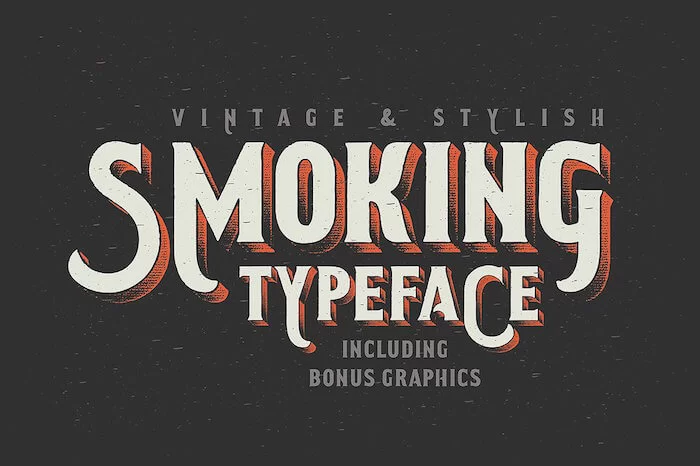
อัลฟ่า สโมค
ด้วยจำนวนสัญลักษณ์ 72 แบบอักษร Alpha Smoke ไม่อยู่ในคลาสครอบครัวที่ระบุ แบบอักษรกึ่งหนานี้มีความกว้างปานกลาง (ปกติ) แบบอักษรเป็นไปตามสไตล์ Mac ตัวหนาและมีลักษณะลวดลายที่ร่างไว้
มีท่ายืนตรงและมีความกว้างปกติ อย่างไรก็ตาม มันไม่ใช่โมโนสเปซ คุณสามารถดาวน์โหลดแบบอักษรนี้ได้ที่นี่
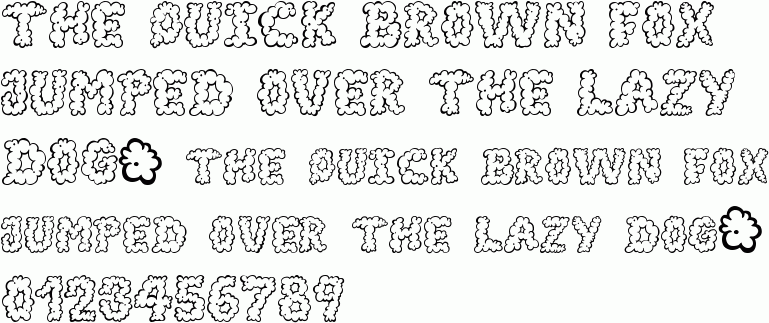
หลังจาก Cheret Bold
แบบอักษรเป็นของตระกูล 'ละติน (ข้อความและจอแสดงผล)' และเป็นไปตามสไตล์ mac ตัวเอียง ไม่อยู่ในกลุ่มครอบครัวที่ระบุใด ๆ และมีน้ำหนักตัวหนา
แบบอักษรมีความกว้างปานกลาง (ปกติ) และมีลวดลายที่เป็นธรรมชาติ มีสัญลักษณ์จำนวน 176 มันไม่ใช่โมโนสเปซ สามารถดาวน์โหลดแบบอักษรนี้ได้ที่นี่
รถไฟของเล่น
แบบอักษรมีจำนวนสัญลักษณ์ 87 แบบอักษรนี้ไม่อยู่ในประเภทครอบครัวที่ระบุและเป็นแบบกึ่งน้ำหนักเบา มีความกว้างปานกลาง (ปกติ) ฟอนต์ตามสไตล์ mac ตัวหนา
สไตล์ serif และรูปแบบ arm สำหรับฟอนต์นั้นยังไม่ได้รับการแก้ไขและสามารถเป็นอะไรก็ได้ แบบอักษรนี้สามารถดาวน์โหลดได้ฟรีที่นี่
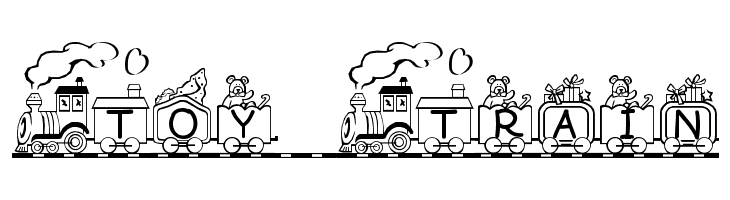
ใบหวาน
ฟอนต์ที่มีสัญลักษณ์จำนวน 219 อันไม่อยู่ในคลาสครอบครัวที่ระบุ เป็นแบบอักษรกึ่งน้ำหนักเบาที่มีความกว้างปานกลาง (ปกติ)
มีรูปแบบของธรรมชาติปกติและไม่เว้นระยะ มันเป็นไปตามสไตล์ Mac ตัวหนาและสามารถดาวน์โหลดได้ ที่นี่
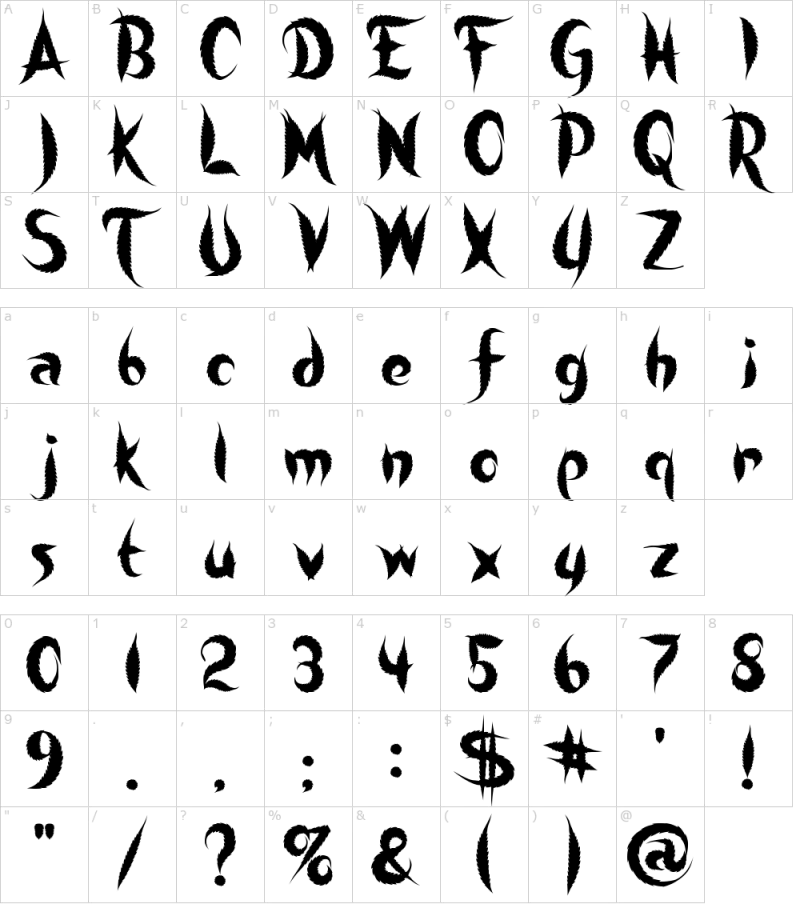
PotLand
แบบอักษรกึ่งน้ำหนักเบานี้เป็นไปตามสไตล์ Mac ตัวหนา ไม่อยู่ในคลาสครอบครัวที่ระบุและมีจำนวนสัญลักษณ์ 219 เป็นแบบอักษรที่ได้รับอนุญาต (มีการป้องกัน) และไม่เว้นวรรค
แบบอักษรนี้มีความกว้างปานกลาง (ปกติ) สามารถดาวน์โหลดได้ที่นี่
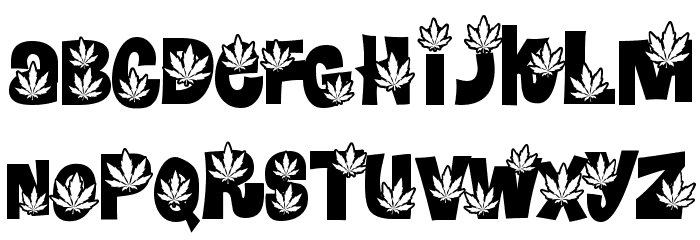
รอยัล อินเฟอร์โน
แบบอักษรเป็นของตระกูล 'ละติน (ข้อความและจอแสดงผล)' และไม่เว้นวรรค มีสัญลักษณ์จำนวน 153 และไม่ได้อยู่ในกลุ่มครอบครัวที่ระบุ
แบบอักษรมีน้ำหนักปานกลาง (ปกติ) และความกว้างกึ่งย่อ มันเป็นไปตามสไตล์ Mac ตัวหนาและมีรูปแบบของธรรมชาติเป็นประจำ ฟอนต์นี้สามารถดาวน์โหลดได้ที่นี่
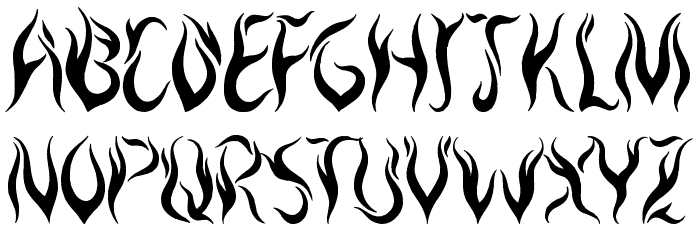
Smoke In The Woods
แบบอักษรมีจำนวนสัญลักษณ์ 91 และอยู่ในคลาสตระกูล 'Slab serifs' มีน้ำหนักตัวหนาและความกว้างที่ควบแน่น มันเป็นไปตามสไตล์ Mac ตัวหนาและมีรูปแบบตัวเอียง
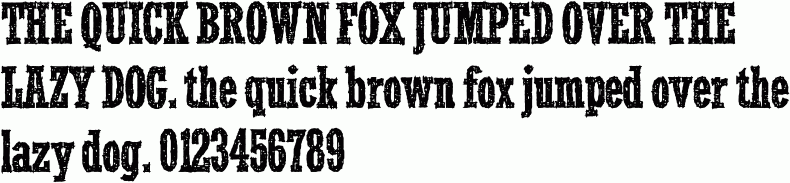
แบบอักษรควัน
นี่คือชุดแบบอักษรควันที่สมบูรณ์ แบบอักษรแต่ละแบบมาแยกกันในไฟล์ PNG ที่มีพื้นหลังโปร่งใส
คุณสามารถดาวน์โหลดแบบอักษรและแก้ไขได้ในโปรแกรมแก้ไขแบบอักษร นี่อาจเป็นตัวเลือกแบบอักษรที่ดี หากคุณต้องการให้งานออกแบบของคุณดูมีควันมากขึ้น
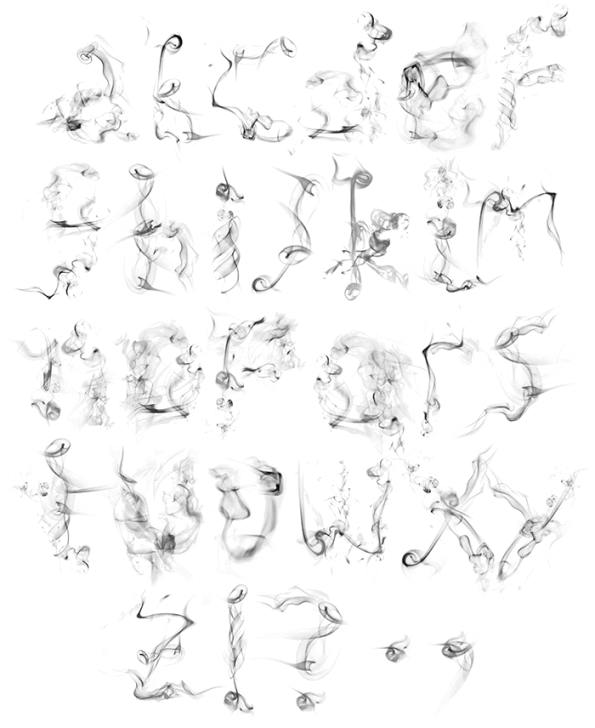
ฝันดีที่เป็นจริง
แบบอักษรนี้เป็นของคลาสตระกูล 'สคริปต์' มีน้ำหนักและความกว้างปานกลาง (ปกติ) มีรูปแบบของธรรมชาติปกติและไม่เว้นระยะ
มีจำนวนสัญลักษณ์ 97 แบบอักษรตามสไตล์ mac ตัวหนา ฟอนต์นี้มาจากตระกูล 'Latin (text and display)' พร้อมให้ดาวน์โหลดฟรีที่นี่
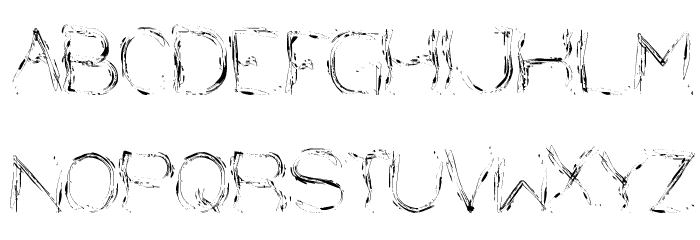
แบบอักษรแสงรบกวนควัน
แบบอักษรมีจำนวนสัญลักษณ์ 119 ซึ่งเป็นสัดส่วนที่ทันสมัยและไม่ได้อยู่ในระดับครอบครัวที่ระบุ แบบอักษรน้ำหนักเบานี้มีความกว้างปานกลาง (ปกติ) และเป็นไปตามสไตล์ Mac ตัวหนา มีรูปแบบของธรรมชาติปกติและไม่เว้นระยะ
ฟอนต์นี้มาจากตระกูล 'Latin (text and display)' สามารถดาวน์โหลดได้ที่นี่ แบบฟอร์มจดหมายเป็นปกติ/ติดต่อ
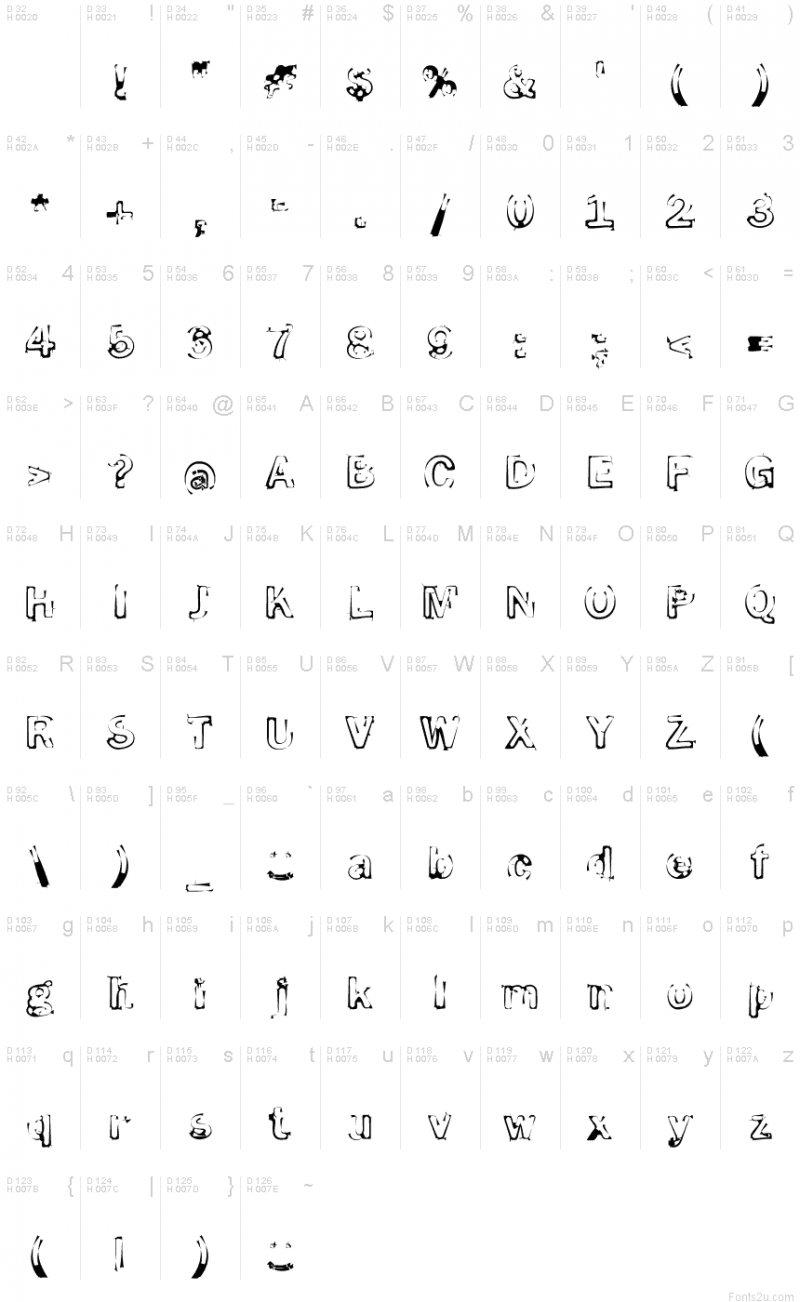
รอยเปื้อน
แบบอักษรนี้เป็นของคลาสตระกูล 'สคริปต์' มีความกว้างปานกลาง (ปกติ) แบบอักษรกึ่งหนานี้มีจำนวนสัญลักษณ์ 102
มันเป็นไปตามสไตล์ Mac ตัวหนาและมีรูปแบบของธรรมชาติเป็นประจำ ไม่เว้นวรรคและมาจากประเภทครอบครัว 'ละติน (ข้อความและจอแสดงผล)' ดาวน์โหลดฟอนต์ที่นี่
ความฝันเก่า
แบบอักษรนี้เป็นของคลาสตระกูล 'Modern serifs' มีน้ำหนักและความกว้างปานกลาง (ปกติ) มีจำนวนสัญลักษณ์ 285 และเป็นไปตามสไตล์ Mac ตัวหนา
ฟอนต์มาจากตระกูล 'Latin (text and display)' มีรูปแบบที่เป็นธรรมชาติและไม่เว้นวรรค คุณสามารถดาวน์โหลดแบบอักษรได้ที่นี่
SmokeShadow ขนาดกลาง
แบบอักษรมีน้ำหนักตัวหนาและมีความกว้างปานกลาง (ปกติ) มีสัญลักษณ์จำนวน 121 และไม่ได้อยู่ในกลุ่มครอบครัวที่ระบุ
มันเป็นไปตามสไตล์ Mac ตัวหนาและมีลักษณะลวดลายที่ร่างไว้ มันไม่ได้เป็นแบบโมโนสเปซและสามารถดาวน์โหลดได้ ที่นี่
ควันคอนทัวร์ตัวเอียง
แบบอักษรเป็นของตระกูล 'ละติน (ข้อความและจอแสดงผล)' ยังไม่มีการกำหนดรูปแบบ serif และรูปแบบปลอกแขนโดยเฉพาะ และสามารถเป็นแบบใดก็ได้ มีสัญลักษณ์จำนวน 119 และไม่ได้อยู่ในกลุ่มครอบครัวที่ระบุ
แบบอักษรตัวหนานี้มีความกว้างปานกลาง (ปกติ) และสามารถดาวน์โหลดได้ที่นี่ นอกจากนี้ แบบอักษรเป็นไปตามสไตล์ Mac ที่ขีดเส้นใต้ มีลักษณะรูปแบบตัวเอียง และไม่เว้นวรรค
Smoke ScreenObl ตัวเอียง
แบบอักษรมีจำนวนสัญลักษณ์ 119 และไม่อยู่ในคลาสครอบครัวที่ระบุ มีน้ำหนักและความกว้างปานกลาง (ปกติ) และเป็นไปตามสไตล์ Mac ที่ขีดเส้นใต้
มีท่ายืนตรงแต่ไม่เว้นระยะ ฟอนต์นี้สามารถดาวน์โหลดได้ที่นี่
แบบอักษร BB ระเหย
การออกแบบฟอนต์แฟนซีที่ให้ความรู้สึกสโมคกี้ มันมีฟอนต์เวอร์ชันปกติและตัวเอียงให้คุณ ดังนั้นคุณจึงสามารถใช้งานได้ตามความต้องการของคุณ คุณสามารถดาวน์โหลดแบบอักษรได้ที่นี่